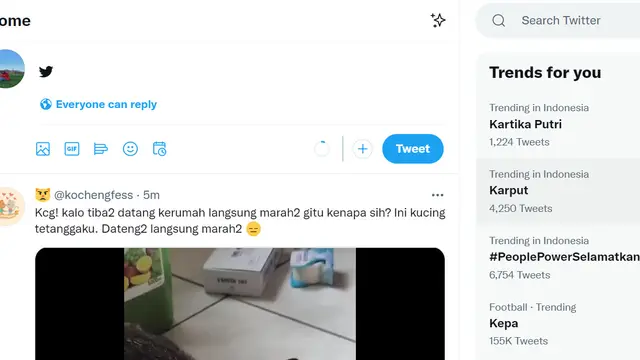
Liputan6.com, Jakarta - Twitter resmi mengubah tampilan font (jenis huruf) di aplikasi maupun Twitter web. Kini, font di Twitter pun seragam untuk semua pengguna Twitter.
Adapun font yang digunakan oleh Twitter untuk aplikasi maupun versi web-nya bernama Chirp font.
Warganet yang menyadari bahwa font Twitter mereka berubah pun kaget dan bertanya-tanya apakah perubahan font ini hanya dialami dirinya atau semua orang.
Perubahan font Twitter menjadi Chirp pun membuat linimasa Twitter ramai. Kata "Font" dan "Berubah" bahkan sempat menjadi trending topic di linimasa Twitter Indonesia.
"Day by day, Twitter makin berubah," cuit seorang pengguna.
day by day twitter makin berubah
— 𝒷𝓎𝓁𝓁 . (@mnabylaaa) August 12, 2021
Pengguna lainnya heran karena font Twitter-nya berubah. "Wait wait wait..kok font type Twitter gue berubah?"
Wait wait wait.. kok font type twitter gue berubah? 🤔
— Dina FA Simbolon (@dinasimbolon_) August 12, 2021
woke up and i just realized that FONT TWITTER BERUBAH ???
— karyn🗯️ (@hugmkle) August 12, 2021
Ada pula warganet yang mempertanyakan apakah perubahan font Twitter ini hanya dialami dirinya atau juga pengguna lain.
wait is it just me or font twitter berubah..?
— fivi (@junshualogy) August 12, 2021
EHHH??? SOMETHING DIFFERENT FROM MY TWITTER....... FONT-NYA BERUBAH
— aya🌻| THUNDEROUS⚡ (@choronasauruzz) August 12, 2021
Resmi Ubah Jenis Huruf Jadi Chirp Font
Sebelumnya, jejaring sosial Twitter menggulirkan font baru bernama Chirp pada aplikasi maupun versi web-nya.
Mengutip The Verge, Kamis (12/8/2021) informasi soal perubahan font Twitter ini sebelumnya sudah diumumkan Twitter melalui akun resmi mereka.
Uniknya, sebagian besar pengguna sudah melihat perubahan font di aplikasi Twitter mereka, namun ada sebagian lainnya yang belum merasakan perubahan font ini.
Twitter merinci, font Chirp merupakan salah satu bagian dari penyegaran brand mereka.
"Chirp menyeimbangkan antara tampilan yang terlihat acak-acakan dan tajam untuk memperkuat kesenangan sekaligus ketajaman sebuah tweet. Namun (font) Chirp juga membawa keseriusan saat dibutuhkan," kata Twitter dalam unggahan blog-nya.
Saat itu, Twitter menggunakan font Chirp untuk materi promosi dan grafik. Namun font ini belum terlihat di feed atau ketika menavigasi aplikasi.
Direktur Kreatif Global Brand Twitter Derrit DeRouen pada Januari lalu mengatakan, merupakan "keinginan pribadinya" untuk menjadikan Chirp sebagai font default untuk produk Twitter. Namun saat itu DeRouen tak menyebut kapan perusahaan akan menggulirkan penggunaan font Chirp pada seluruh pengguna.
Perubahan Lainnya
"Kami juga memperbarui warna dengan kontras yang lebih tinggi dan jauh lebih biru. Perubahan ini dibuat untuk menarik perhatian pada foto dan video yang Anda bagikan," kata Twitter dalam utas yang diunggahnya.
Perusahaan berjanji meluncurkan warna baru dalam waktu dekat. Disebutkan pula, mereka yang sudah berlangganan layanan premium Twitter Blue sudah bisa mengubah warna aplikasi dan mengubah warna ikon aplikasi, namun layanan premium ini baru tersedia untuk pengguna iOS di Kanada dan Australia.
Bukan hanya itu, selain mengubah font, Twitter juga mengubah tampilan tombol Follow. Kini ketika pengguna telah mengikuti sebuah akun, latar belakang tombol Follow berwarna putih, sementara ketika belum mengikuti sebuah akun, tulisan Follow hadir dengan background hitam.
Ini merupakan kebalikan dari cara kerja tombol Follow yang sebelumnya, jadi pengguna perlu berhati-hati agar tidak salah meng-unfollow sebuah akun.